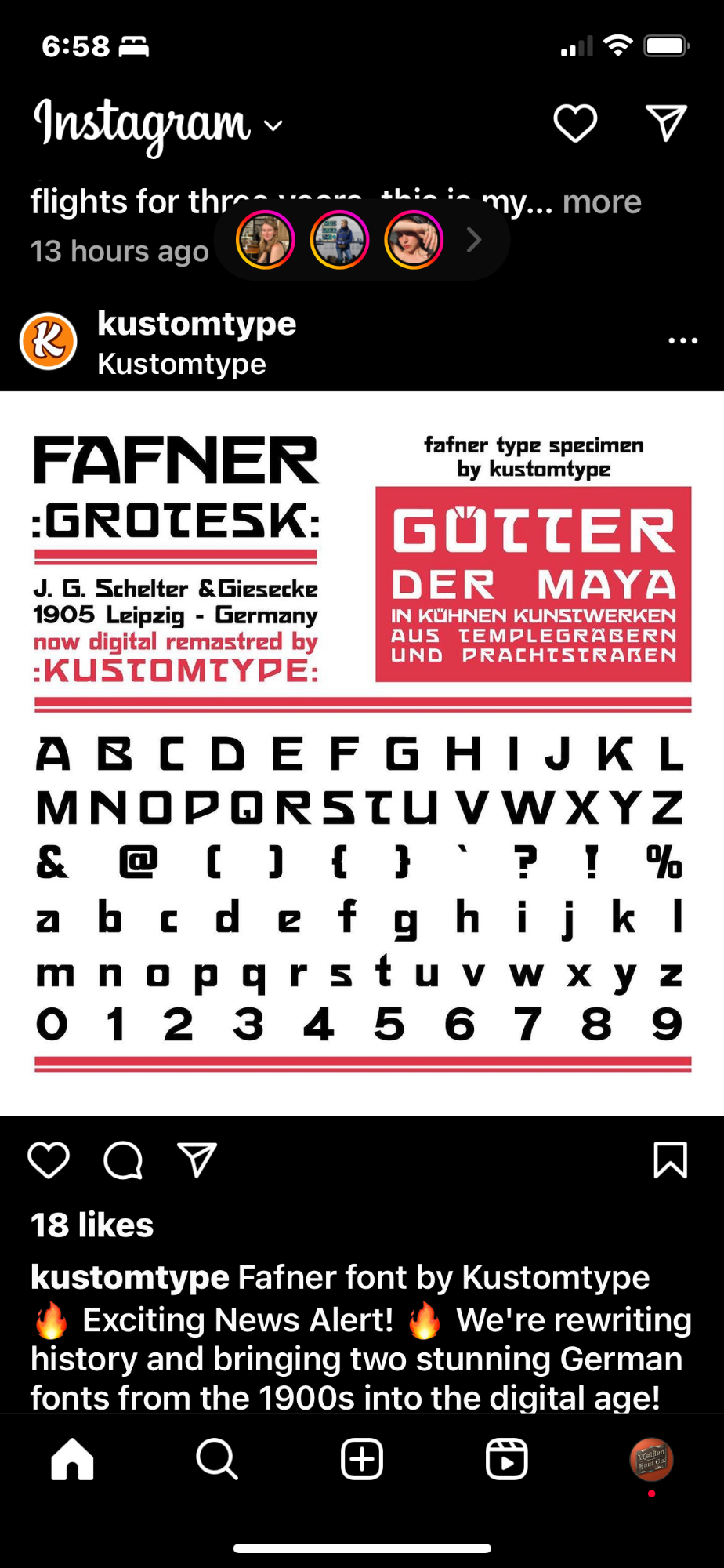
We are not amused 😡
Heute früh sah ich auf Instagram die folgende Bekanntmachung:
Fafner gibt es von mir schon seit zwei Jahren. Naja, es steht ihm natürlich frei, sich seine eigene Version zu drechseln, solange er sich auf das Quellenmaterial bezieht. Das @ sieht meinem aber verteufelt ähnlich.
Dann kommt aber der Hammer: Das Beispiel "Götter der Maya" ist nämlich direkt (samt Tippfehler) aus meiner Probe geklaut! Da hat er wohl wild gegoogelt und sich nicht um die Herkunft seiner Quellen gekümmert. Normalerweise finde ich solche Sachen zum lachen, aber das hier ist wie ein Schlag ins Gesicht 😡
Ich habe ihn natürlich gleich darauf hingewiesen. Mal sehen, was passiert.
Übrigens war seine Quellenarbeit schon früher schlampig. Vor ein paar Jahren hat er voller Begeisterung ein Revival von Quick/Trafton Script vorgestellt. Er sagte dazu, er hätte diese schöne, namenlose Schrift irgendwo gefunden und wußte nicht, daß sie schon mehrfach digitalisiert wurde. 😬
Edit: meine Version:
Du bist aber nicht der einzige; auch bei anderen Schriften hat er keine Quellenangaben gemacht. Die Jackson, etwas weiter unten, ist bei fontsinuse mit allen Quellen angegeben. Bei ihm: nichts. 🤮
Hmm, ich würde mir die Outlines und Kerning-Tables der Schriften mal anschauen … nicht dass es da auffällig viele Übereinstimmungen gibt.
Aus Business-Sicht finde ich das sensationell: eine Schrift auf den Markt bringen, die kurz zuvor schonmal von jemanden herausgebracht wurde.
Markt-Analyse = null!